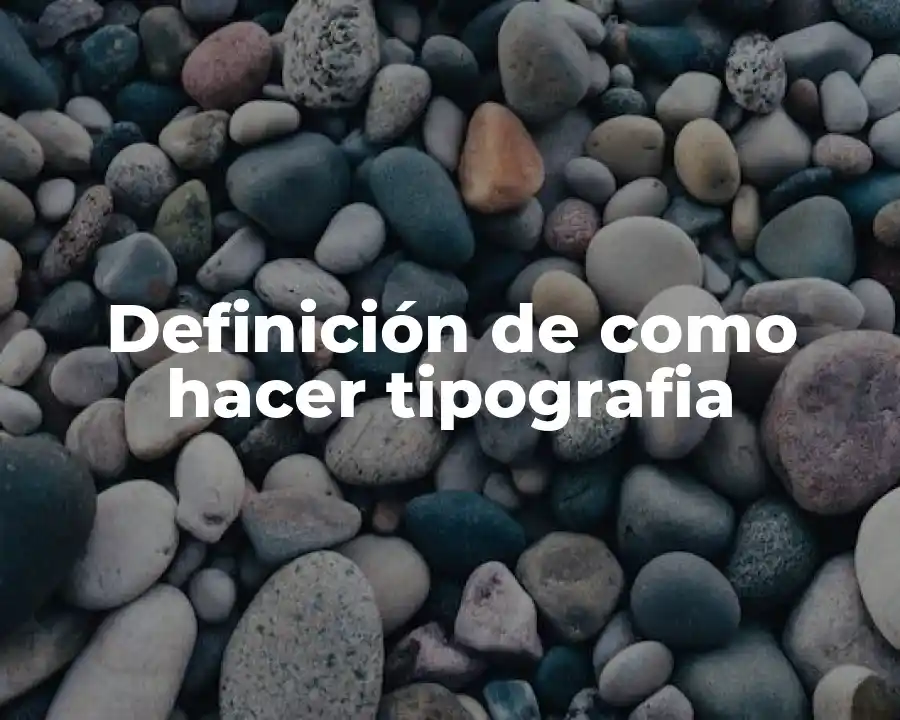
En este artículo, vamos a explorar el tema de la tipografía y cómo se puede aplicar en diferentes contextos. La tipografía es una parte fundamental del diseño gráfico, y es importante entender cómo se puede utilizar de manera efectiva para comunicar mensajes y transmitir información.
¿Qué es como hacer tipografia?
La tipografía es el arte y la ciencia de crear y manipular textos para lograr un efecto visual y comunicativo. Se refiere a la elección y arreglo de los caracteres tipográficos, como la fuente, el tamaño, el color y el estilo, para transmitir un mensaje o crear un efecto emotivo. La tipografía es un aspecto fundamental del diseño gráfico y es utilizada en una variedad de campos, desde la publicidad y la comunicación hasta la literatura y el arte.
Ejemplos de como hacer tipografia
- Ejemplo 1: Títulos: La elección de la fuente y el tamaño de los caracteres es crucial para los títulos y subtítulos. Un título bien diseñado puede atrapar la atención del lector y transmitir la esencia del contenido.
- Ejemplo 2: Cuerpos de texto: La elección de la fuente y el tamaño de los caracteres también es importante para el cuerpo del texto. Un estilo de letra claro y legible puede hacer que el texto sea fácil de leer y comprender.
- Ejemplo 3: Negrita y cursiva: La negrita y la cursiva pueden ser utilizadas para destacar palabras o frases importantes. La negrita puede ser utilizada para enfatizar la importancia de un texto, mientras que la cursiva puede ser utilizada para indicar un cambio en el estilo o tono.
- Ejemplo 4: Colores y fondos: La elección de colores y fondos también es importante en la tipografía. Los colores y fondos pueden ser utilizados para transmitir un mensaje o crear un efecto emotivo.
- Ejemplo 5: Alineación: La alineación del texto también es importante en la tipografía. La alineación correcta puede hacer que el texto sea fácil de leer y comprender.
- Ejemplo 6: Espaciado: El espaciado entre las líneas de texto también es importante en la tipografía. Un espaciado adecuado puede hacer que el texto sea fácil de leer y comprender.
- Ejemplo 7: Margen: El margen también es importante en la tipografía. Un margen adecuado puede hacer que el texto sea fácil de leer y comprender.
- Ejemplo 8: Font sizes: La elección del tamaño de los caracteres también es importante en la tipografía. Un tamaño de letra adecuado puede hacer que el texto sea fácil de leer y comprender.
- Ejemplo 9: Line spacing: El espacio entre las líneas de texto también es importante en la tipografía. Un espacio entre las líneas adecuado puede hacer que el texto sea fácil de leer y comprender.
- Ejemplo 10: Kerning: La kerning es la espaciación entre dos caracteres. La kerning también es importante en la tipografía, ya que puede afectar la legibilidad del texto.
Diferencia entre como hacer tipografia y diseño gráfico
La tipografía y el diseño gráfico son dos conceptos relacionados pero diferentes. La tipografía se refiere específicamente al diseño y la elección de los caracteres tipográficos, mientras que el diseño gráfico se refiere a la creación de elementos visuales que comunican un mensaje o transmiten información. Aunque la tipografía es una parte importante del diseño gráfico, no se limita exclusivamente a ella.
¿Cómo se puede aplicar como hacer tipografia en la vida cotidiana?
La tipografía se puede aplicar en la vida cotidiana de muchas maneras. Por ejemplo, se puede utilizar para crear carteles y letreros en la calle, para diseñar folletos y materiales de marketing, o para crear una presentación en PowerPoint. Además, se puede utilizar para crear una identidad visual para una empresa o marca, lo que puede ayudar a comunicar el mensaje y la esencia de la marca.
¿Qué son algunas características de como hacer tipografia?
Algunas características importantes de la tipografía son la elección de la fuente, el tamaño y el estilo de los caracteres, la alineación y el espaciado del texto, y la elección de colores y fondos. La creación de un estilo tipográfico coherente y consistente puede ayudar a transmitir un mensaje o crear un efecto emotivo.
¿Cuándo se debe utilizar como hacer tipografia?
Se debe utilizar la tipografía en cualquier situación en la que se desee comunicar un mensaje o transmitir información de manera efectiva. Por ejemplo, se puede utilizar en carteles y letreros, en materiales de marketing y publicidad, en presentaciones y documentos, o en sitios web y aplicaciones móviles.
¿Qué son algunos ejemplos de como hacer tipografia en la vida cotidiana?
Algunos ejemplos de como hacer tipografia en la vida cotidiana son:
- Ejemplo 1: Carteles y letreros: La tipografía se puede utilizar para crear carteles y letreros en la calle que transmitan un mensaje o advertan sobre un evento.
- Ejemplo 2: Materiales de marketing: La tipografía se puede utilizar para crear materiales de marketing y publicidad que atraigan la atención del público y comuniquen un mensaje.
- Ejemplo 3: Presentaciones: La tipografía se puede utilizar para crear presentaciones en PowerPoint o Keynote que comuniquen un mensaje o transmitan información de manera efectiva.
- Ejemplo 4: Sitios web: La tipografía se puede utilizar para crear sitios web y aplicaciones móviles que comuniquen un mensaje o transmitan información de manera efectiva.
Ejemplo de como hacer tipografia de uso en la vida cotidiana?
Un ejemplo de como hacer tipografia de uso en la vida cotidiana es la creación de una cartelera para un evento. Se puede utilizar una fuente de letra clara y legible, como Arial o Helvetica, y se puede elegir un tamaño de letra adecuado para que el texto sea fácil de leer. Se puede utilizar un color de fondo y letra contrastado para hacer que el texto sea visible y atractivo. Se puede agregar un título y subtítulos para hacer que el texto sea más atractivo y fácil de leer.
Ejemplo de como hacer tipografia desde una perspectiva diferente
Un ejemplo de como hacer tipografia desde una perspectiva diferente es la creación de un cartel para un concierto de música. Se puede utilizar una fuente de letra más artística y creativa, como Impact o Brush Script, y se puede elegir un tamaño de letra grande y llamativo para atraer la atención del público. Se puede utilizar un color de fondo y letra vibrante y llamativo para hacer que el texto sea visible y atractivo. Se puede agregar imágenes y logotipos para hacer que el cartel sea más atractivo y interesante.
¿Qué significa como hacer tipografia?
La palabra tipografía proviene del griego typos que significa impronta y graphein que significa escribir. En su sentido más amplio, la tipografía se refiere a la creación y manipulación de textos para lograr un efecto visual y comunicativo.
¿Cuál es la importancia de como hacer tipografia en la comunicación?
La importancia de la tipografía en la comunicación es que puede ayudar a transmitir un mensaje o crear un efecto emotivo. La elección de la fuente, el tamaño y el estilo de los caracteres, la alineación y el espaciado del texto, y la elección de colores y fondos pueden afectar la legibilidad y la comprensión del texto. La tipografía también puede ayudar a transmitir un mensaje o crear un efecto emotivo, lo que puede ser importante en la comunicación efectiva.
¿Qué función tiene como hacer tipografia en la publicidad?
La función de la tipografía en la publicidad es crear un mensaje o transmitir información de manera efectiva. La elección de la fuente, el tamaño y el estilo de los caracteres, la alineación y el espaciado del texto, y la elección de colores y fondos pueden afectar la legibilidad y la comprensión del texto. La tipografía también puede ayudar a transmitir un mensaje o crear un efecto emotivo, lo que puede ser importante en la publicidad.
¿Cómo se puede utilizar como hacer tipografia en la creación de una marca?
La creación de una marca se puede utilizar la tipografía para comunicar el mensaje y la esencia de la marca. La elección de la fuente, el tamaño y el estilo de los caracteres, la alineación y el espaciado del texto, y la elección de colores y fondos pueden afectar la legibilidad y la comprensión del texto. La tipografía también puede ayudar a transmitir un mensaje o crear un efecto emotivo, lo que puede ser importante en la creación de una marca.
¿Origen de como hacer tipografia?
El origen de la tipografía se remonta a la antigüedad, cuando los artesanos griegos y romanos crearon y manipularon textos para lograr un efecto visual y comunicativo. La tipografía se ha desarrollado a lo largo de la historia, y hoy en día se utiliza en una variedad de campos, desde la publicidad y la comunicación hasta la literatura y el arte.
¿Características de como hacer tipografia?
Algunas características importantes de la tipografía son:
- Elección de la fuente: La elección de la fuente es importante en la tipografía, ya que puede afectar la legibilidad y la comprensión del texto.
- Tamaño de letra: El tamaño de letra también es importante en la tipografía, ya que puede afectar la legibilidad y la comprensión del texto.
- Estilo de letra: El estilo de letra también es importante en la tipografía, ya que puede afectar la legibilidad y la comprensión del texto.
- Alineación y espaciado: La alineación y el espaciado del texto también son importantes en la tipografía, ya que pueden afectar la legibilidad y la comprensión del texto.
- Colores y fondos: La elección de colores y fondos también es importante en la tipografía, ya que puede afectar la legibilidad y la comprensión del texto.
¿Existen diferentes tipos de como hacer tipografia?
Sí, existen diferentes tipos de tipografía, como:
- Tipografía en línea: La tipografía en línea se refiere a la creación y manipulación de textos en línea, como en sitios web y aplicaciones móviles.
- Tipografía en impresión: La tipografía en impresión se refiere a la creación y manipulación de textos en impresos, como en carteles y letreros.
- Tipografía en digital: La tipografía en digital se refiere a la creación y manipulación de textos en digitales, como en presentaciones y documentos.
A que se refiere el término como hacer tipografia y cómo se debe usar en una oración
El término tipografía se refiere a la creación y manipulación de textos para lograr un efecto visual y comunicativo. Se debe usar el término tipografía en una oración para describir la creación y manipulación de textos, como por ejemplo: La tipografía es un arte y una ciencia importante para la comunicación efectiva.
Ventajas y desventajas de como hacer tipografia
Las ventajas de la tipografía son:
- Legibilidad y comprensión: La tipografía puede ayudar a mejorar la legibilidad y la comprensión del texto.
- Efecto visual: La tipografía puede crear un efecto visual atractivo y llamativo.
- Comunicación efectiva: La tipografía puede ayudar a comunicar un mensaje de manera efectiva.
Las desventajas de la tipografía son:
- Mala legibilidad: La tipografía mal diseñada puede ser difícil de leer.
- Efecto negativo: La tipografía mal diseñada puede crear un efecto negativo y desagradable.
- Comunicación inefectiva: La tipografía mal diseñada puede no ser efectiva para comunicar un mensaje.